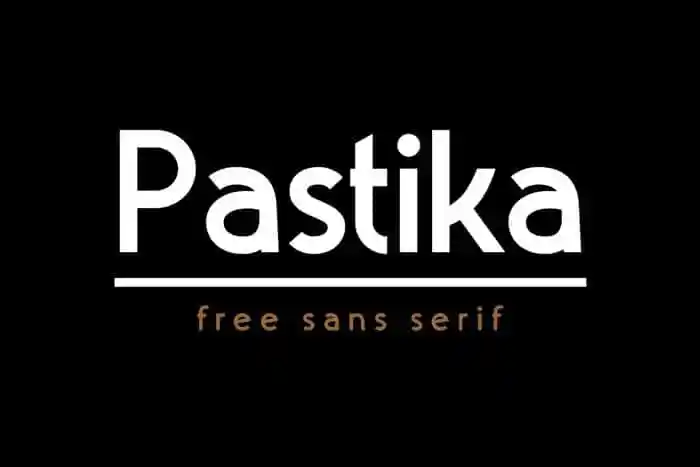
Pastika Sans Serif Font – Download Grátis
A Pastika Sans Serif é uma tipografia com formas disruptivas inspirada na estética tecnológica dos anos 80 e 90 quando havia um estilo próprio para ver o futuro. Esta fonte toma sua estrutura de títulos antigos como Windsor ou Cooper, criando um tipo realmente brincalhão perfeito para cobrir vários projetos, desde revistas e marcas de marca até convites de casamento, camisetas, logotipos e muito mais. Perfeita tanto para designers quanto para amantes da arte visual que desejam dar um toque único a seus projetos. A Pastika Sans Serif é uma escolha ótima para aqueles que buscam uma combinação de clássico com contemporâneo em suas criações visuais.